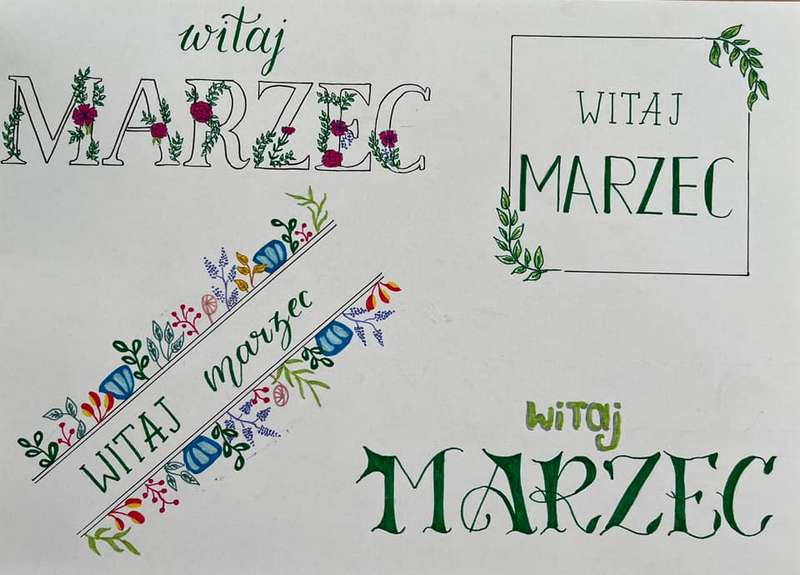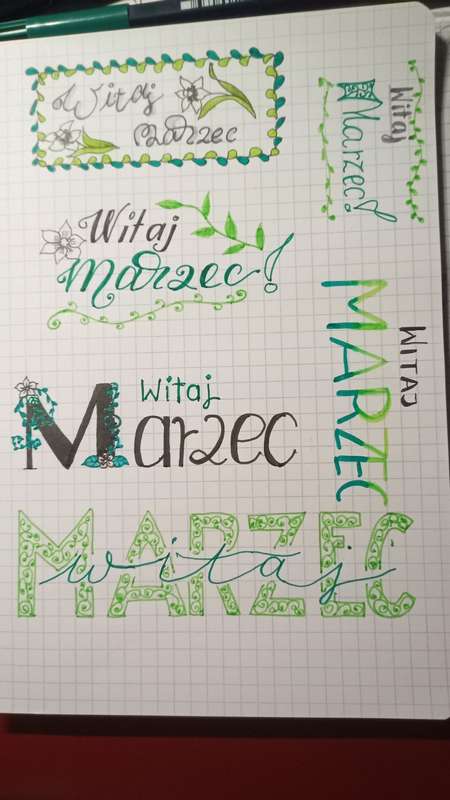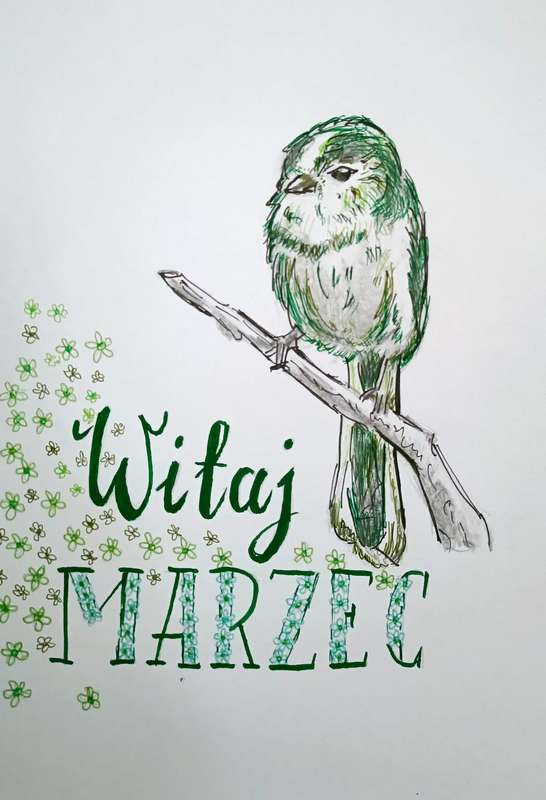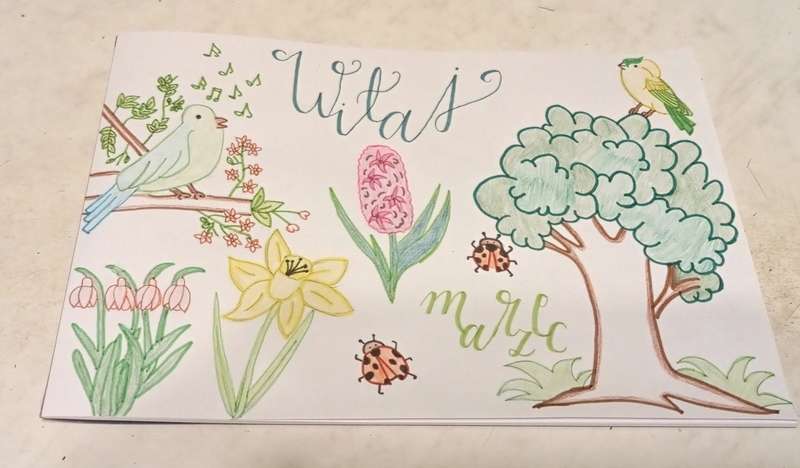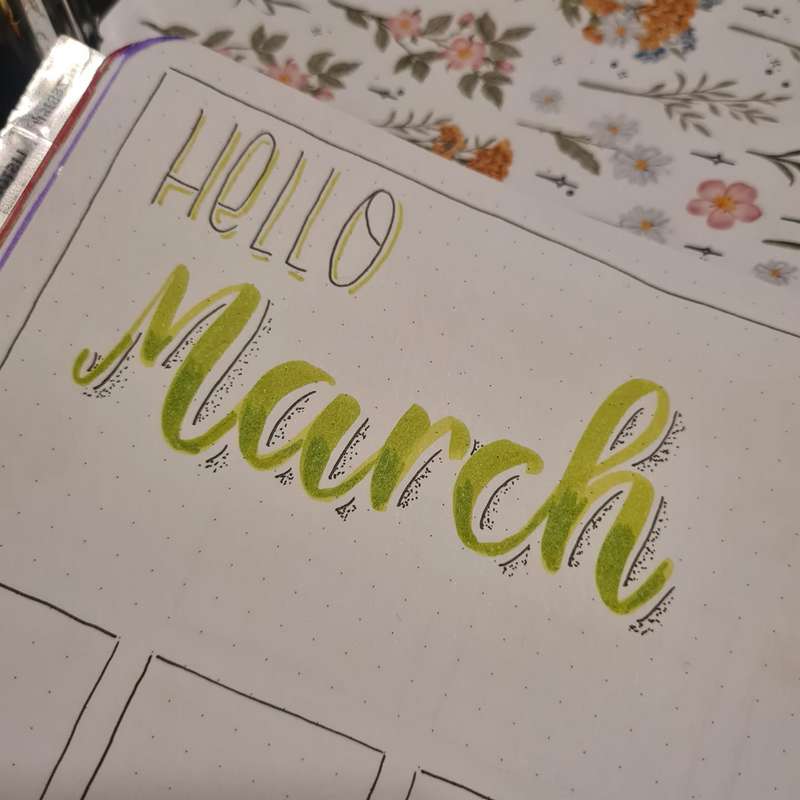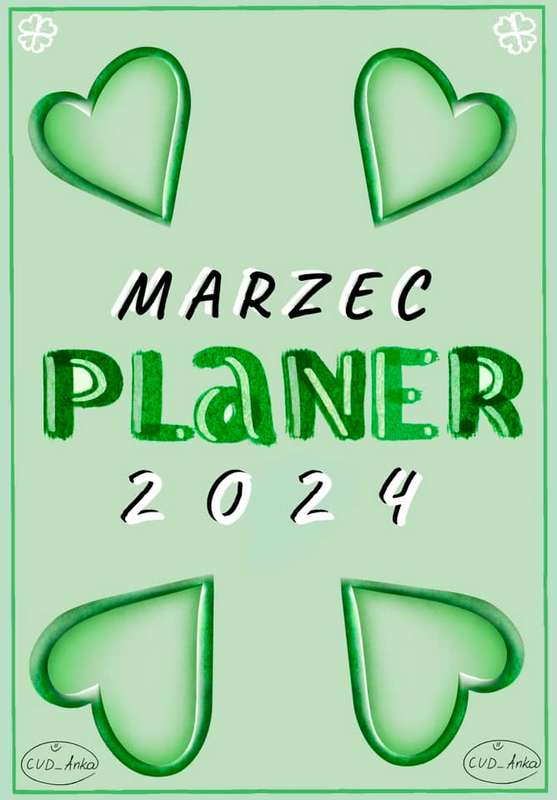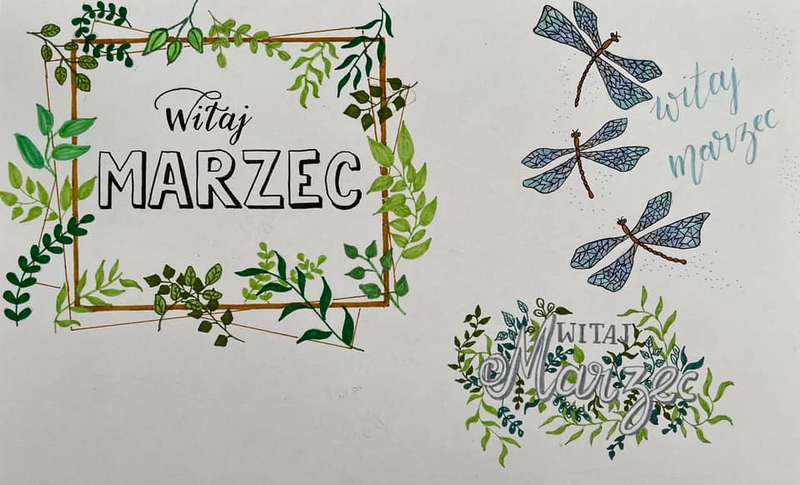
Wiosno przybywaj – zielony marzec [wyzwanie letteringowe]
Już jest MARZEC 💚 niech się zazieleni w internecie 💚
Ostatnio złapała mnie niemoc, brak energii, ciągłe zmęczenie. Jednak myśl o nadciągającym „zielonym marcu” stawia mnie energetycznie na nogi 😀 cieszę się, że mogę znowu coś rysować i tworzyć, a przy tym zarażać innych do tego fajnego hobby. Wiosna ma w ogóle coś magicznego w sobie 💚💚💚
Nie chce ci się, albo nie wiesz, jak zacząć? Spróbuj odtworzyć inne prace, zainspiruj się. Poświęć sobie 10-15 minut na jedno hasło. I przede wszystkim nie wymagaj od siebie perfekcji.
✅Jaka jest recepta na udany projekt? Radość tworzenia!
✅Jeśli te 10-15 minut cię odciągną cię od dnia codziennego, wywołają zadowolenienie i radość, to jest idealny projekt. Bo na sam koniec to tylko jakiś tam napis. Ale czas podczas tworzenia jest bezcenny.
Wykonaj pierwsze hasło z naszego zielonego Marca i wrzuć w grupie.
A tutaj przegląd pierwszych pięknych prac:
Piękne kwieciste wzory to specjalność Marceliny. Zwróć uwagę, jak pięknie udekorowała litery:
(od lewej) Klaudia eksperymentuje z różnymi krojami pisma, natomiast Mar Gu (po prawej) podpisuje swoje piękne ilustracje kwiecistymi literami.
Paulina (od lewej) z kolei wykorzystała powitanie marca w swoim BuJo, a CUD_Anka (po prawej) wykonała w Procreate swoją stronę tytułową planera.
Anna z kolei uroczyście przywitała marzec pięknymi ilustracjami zwiastującymi wiosnę 🙂